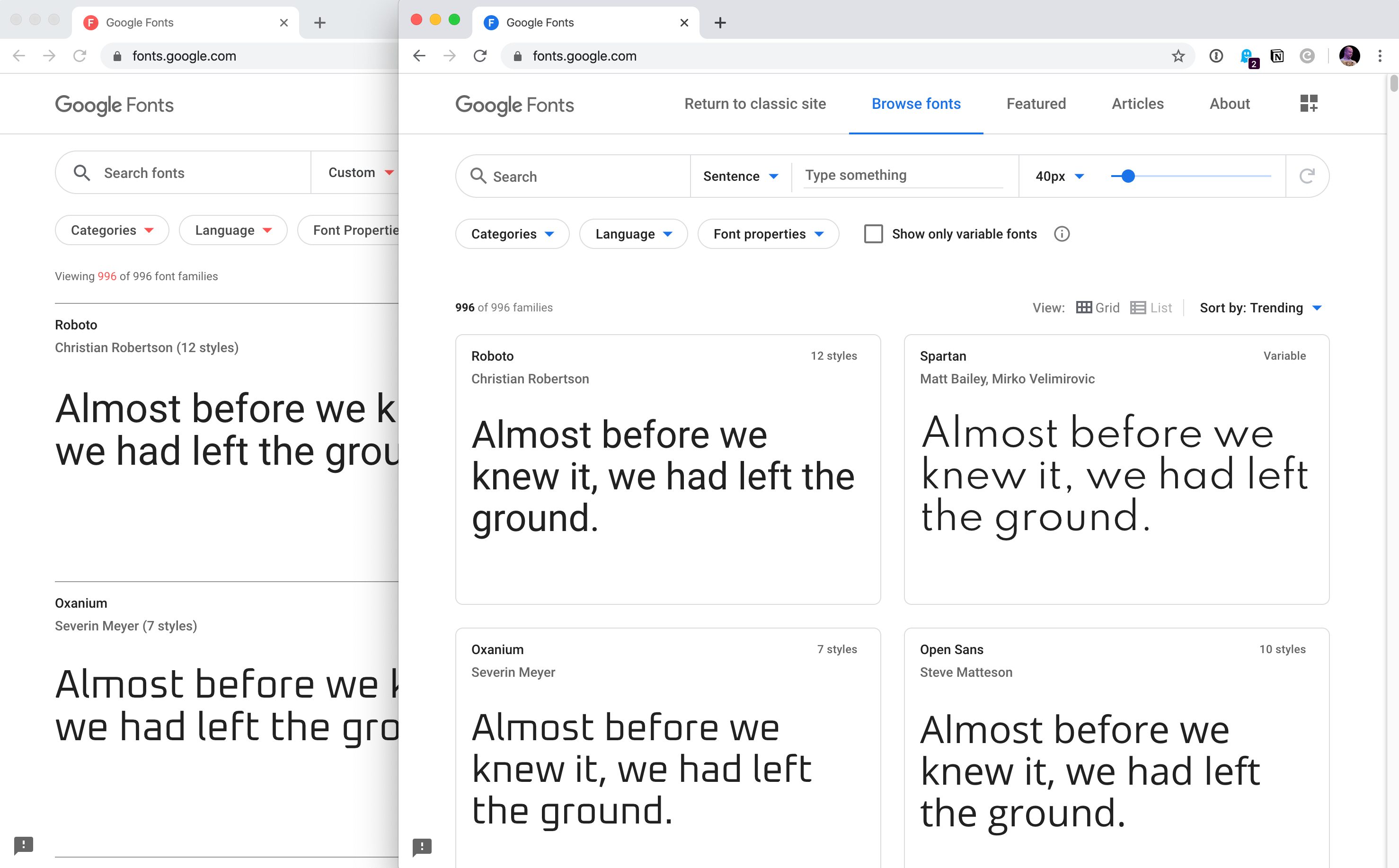
Вы ищете лучшие шрифты Google которые вы можете использовать в своем блоге? Мы перечислили лучшие шрифты в этой статье.
Создание веб-сайта, на котором для того, чтобы опубликовать себя в мире, открыть себя миру, может быть волнующим и в то же время довольно ошеломляющим.
В наше время, когда глобальная сеть переполнена похожим контентом и услугами, крайне важно, чтобы ваш контент отличался от других и мгновенно привлекал внимание.
Для этого также важно понимать, насколько важна литературная реклама. Поэтому мы предлагаем вам широкий спектр Google шрифтов для веб-сайтов, которые сделают ваши заголовки популярными и привлекут трафик, которого заслуживает ваш контент.
Запустив в 2010 году, Google шрифтов неуклонно получали признание, поскольку они широко использовались профессионально и лично.
Когда вы размещаете свои идеи и контент, его удобочитаемость имеет первостепенное значение.
Сложные шрифты могут хорошо выглядеть на бумаге, но могут не передать ваше сообщение, потому что их не так легко сразу понять.
Вам нужно что-то, что запомнится зрителям с первого взгляда. Здесь мы собрали исчерпывающую список шрифтов Google это поможет вашему блогу или веб-сайту привлечь больше внимания.
Кроме того, пришло время нарушить монотонность Times New Roman и пробудить немного рвения, сохраняя при этом доверие к себе!
Open Sans
Один из самых популярных и широко используемых шрифтов Google, Open Sans — это шрифт без засечек, разработанный Стивом Маттесоном.
Простой и чистый дизайн шрифта Open Sans делает его популярным среди блоггеров и писателей. Даже Google использует шрифты Open Sans для количества своих страниц.
- Оптимизирован для печати
- Идеально подходит для мобильных устройств
- Популярен среди блогеров
Lato
Lato — еще один широко используемый шрифт с открытым исходным кодом.
Первоначально разработанный как корпоративный шрифт, этот шрифт с засечками был разработан в 2010.
- Открыт для публики
- Доступны различные версии
- Хороший вариант для блогов
Этот шрифт упивается своей тонкостью. Он очень скромный и пропорциональный, что делает его успокаивающим для человеческого глаза. Он совместим со всеми шестерками, а также когда он ободренный or выделены курсивом.
Это важно, потому что позволяет модерировать заголовки по своему усмотрению, не беспокоясь о том, как это может выглядеть.
- Имеет 8 стилей
- Может использоваться и для небольших размеров шрифта.
- Мясистые и темные буквы
Бри Зериф шрифтШрифт Bree Serif мягкий по краям, что придает ему элегантный и утонченный вид. Это вполне подходящий шрифт, если вы хотите выделить определенные ключевые слова или привлечь внимание к определенным фразам или предложениям.
Он широко используется для заголовков или подзаголовков, так как предложения выделяются.
- Строго вертикально
- Самый популярный в США
- Сразу же получил предпочтение после выхода в 2008 году.
Droid шрифтБратство Droid состоит из Droid Sans, Droid Serif и Sans Mono и одинаково совместимо со всеми типами контента с точки зрения абзацев, заголовков, подзаголовков или крылатых фраз.
Они тонкие и острые, но когда они выделены жирным шрифтом, они красиво заполняют пространство, чтобы привлечь ваше внимание. Его можно использовать вместо Джорджии или Верданы Microsoft Word.
- Распространение по трем категориям
- Универсальный с несколькими вариантами
- Привлекательный
Шрифт Барлоу
Barlow — еще один высококачественный бесплатный шрифт Google, который вы можете использовать на своем веб-сайте, а также в любом другом проекте. Этот шрифт выглядит четким, удобным для читателей.
Мы использовали этот шрифт на нашем дочернем сайте, и он выглядит великолепно.
Мы используем этот шрифт для названий и заголовков. Этот шрифт представлен в нескольких различных версиях: полужирный, полужирный и сокращенный. Итак, у вас есть разнообразие, необходимое для вашего проекта.
Кабина шрифтЭтот шрифт может сочетаться с любой обстановкой или фоном и обеспечит такое же ощущение ясности и разборчивости.
Увеличение или уменьшение его размера не повлияет на его удобочитаемость, что даст вам больше творческой свободы для изучения ваших идей и их эффективного воплощения.
Кабина также четкая и точная, что дает формальный вид, если ваш веб-сайт или блог потворствует организация бизнеса или корпорация аудитория или те, у кого очень мало терпимости к причудливому письму.
- Монотонное распределение веса
- Четкие и точные надписи
- Оптически скорректированные кривые
Омар шрифтКаким бы причудливым ни было название, шрифт по умолчанию выделен курсивом.
Он также естественно выделен жирным шрифтом, и дополнительное выделение его жирным шрифтом в дополнение к курсиву наверняка вызовет некоторый интерес или внимание.
Oswald
Oswald также был разработан Верноном Адамсом и запущен в 2011 году. В 2016 году Калапи Гаджар и Алексей Ваняшин улучшили семейство шрифтов для поддержки кириллических символов. На данный момент около 900 миллиардов просмотров, это шрифт, который вы должны рассмотреть, прежде чем принимать решение.
Poppins
Poppins — это геометрический шрифт без засечек, который можно использовать в тексте или отображаемых контекстах, созданных компанией Indian Type Foundry. Это также первый шрифт в нашем каталоге, поддерживающий систему деванагари.